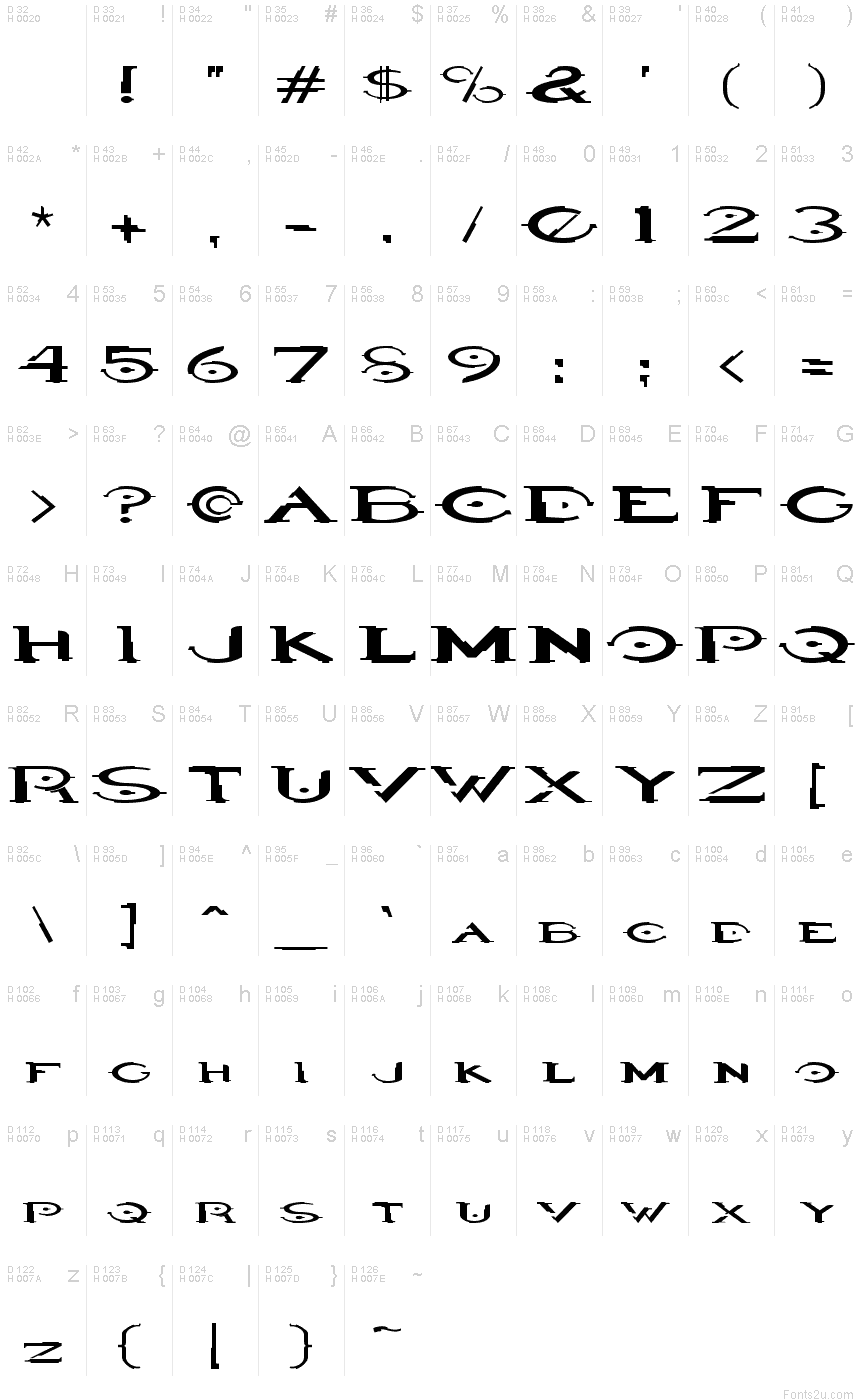
Il font Halo è un carattere futuristico gratuito per titoli cinematografici che trasforma ogni parola in un elemento di branding d'impatto. Le sue aste alte e rigide si scontrano con contrografie circolari simili a bersagli e bordi affilati con staffe, creando uno strano mix di rituale arcano e tecnologia sci-fi. Le lettere sembrano incise nel metallo: nitide, pesanti e leggermente minacciose, rendendo persino una parola breve un logo a sé stante.
Usare Halo per titoli grandi e ariosi su poster, intro di film, copertine di giochi, titoli di libri ed eventi permette alle sue forme scolpite di respirare davvero. Questo font gratuito funziona a meraviglia anche sul merchandising tematico, dalle magliette alle carte da collezione; basta abbinarlo a un semplice sans serif geometrico nel testo più piccolo per garantire la leggibilità, lasciando a Halo il compito di creare il dramma.
Halo